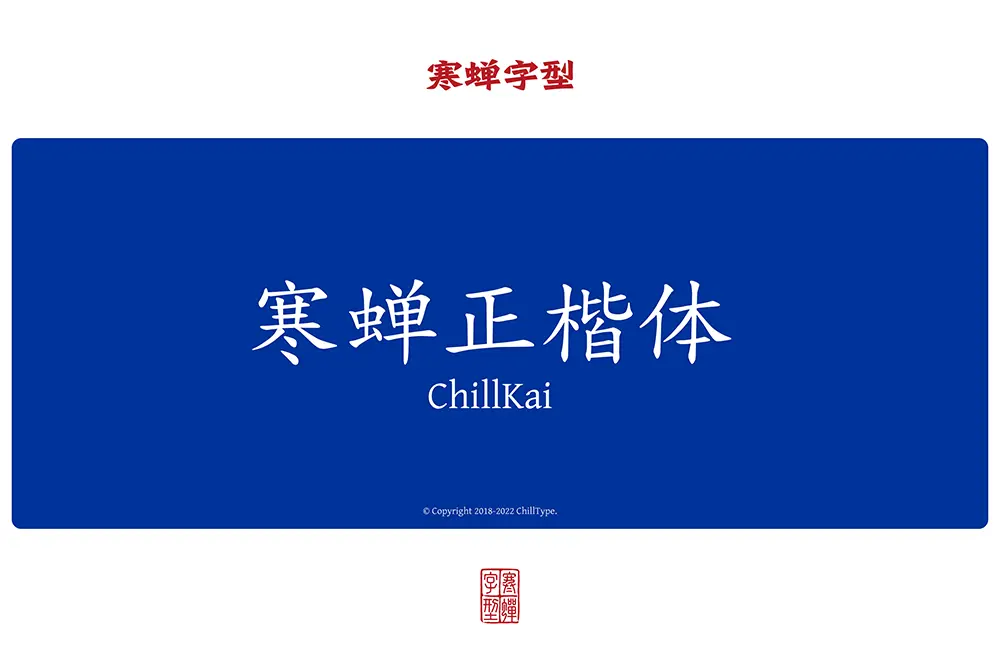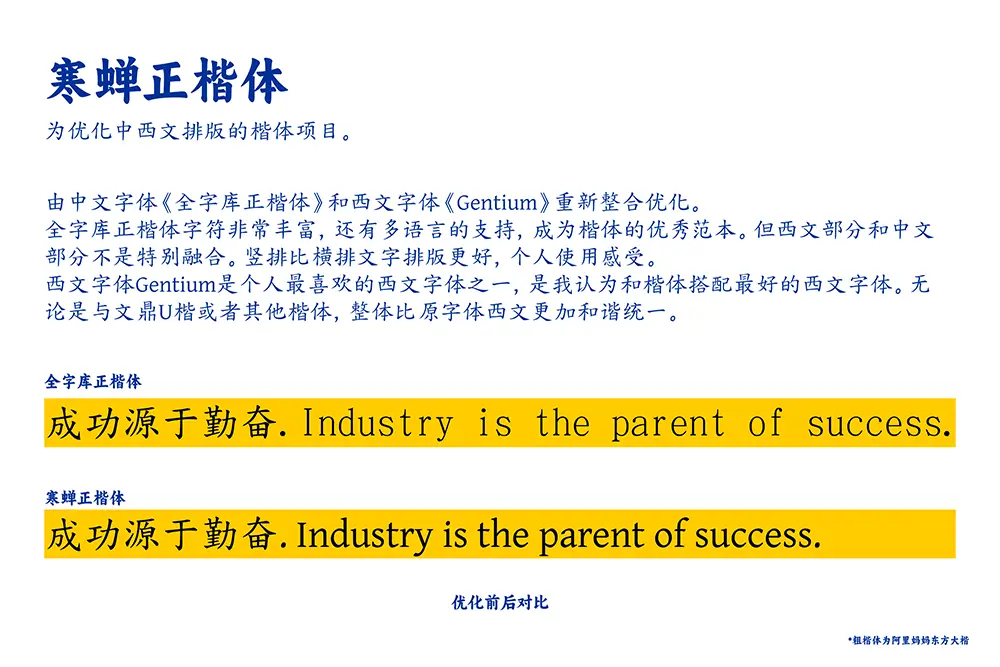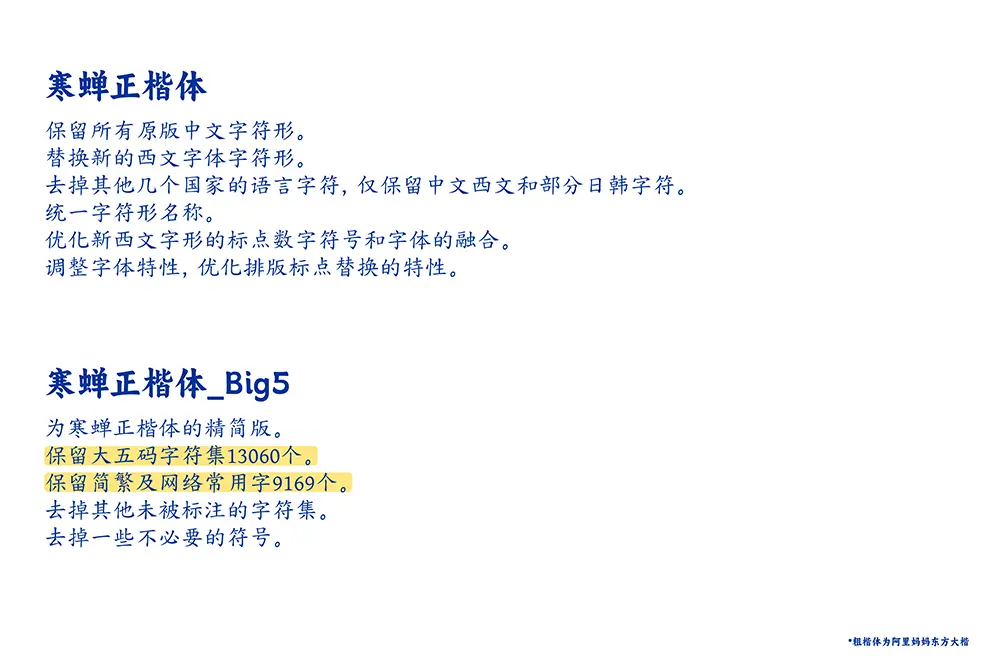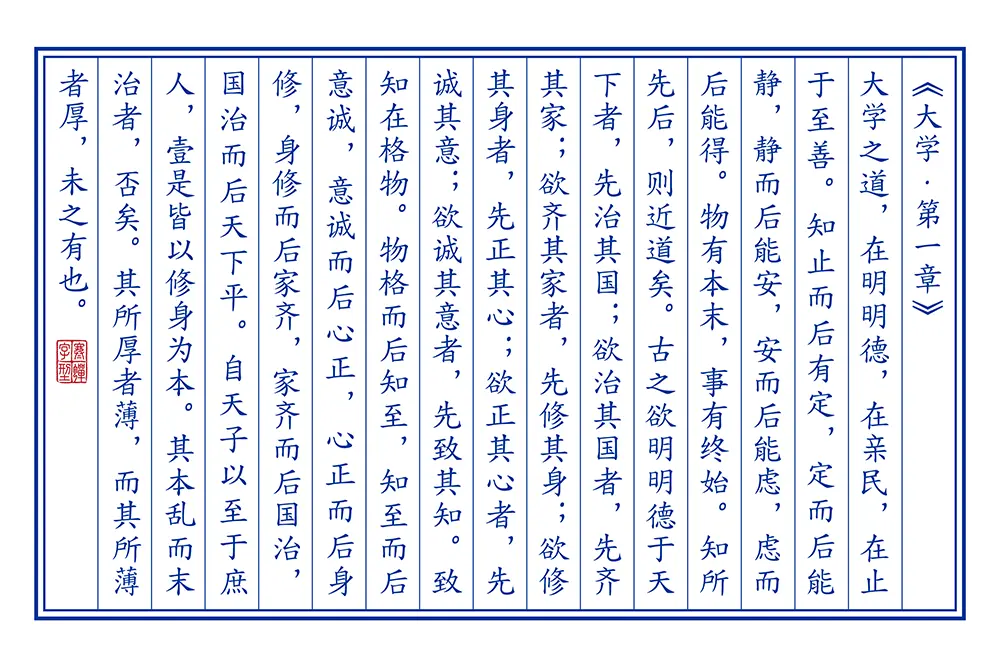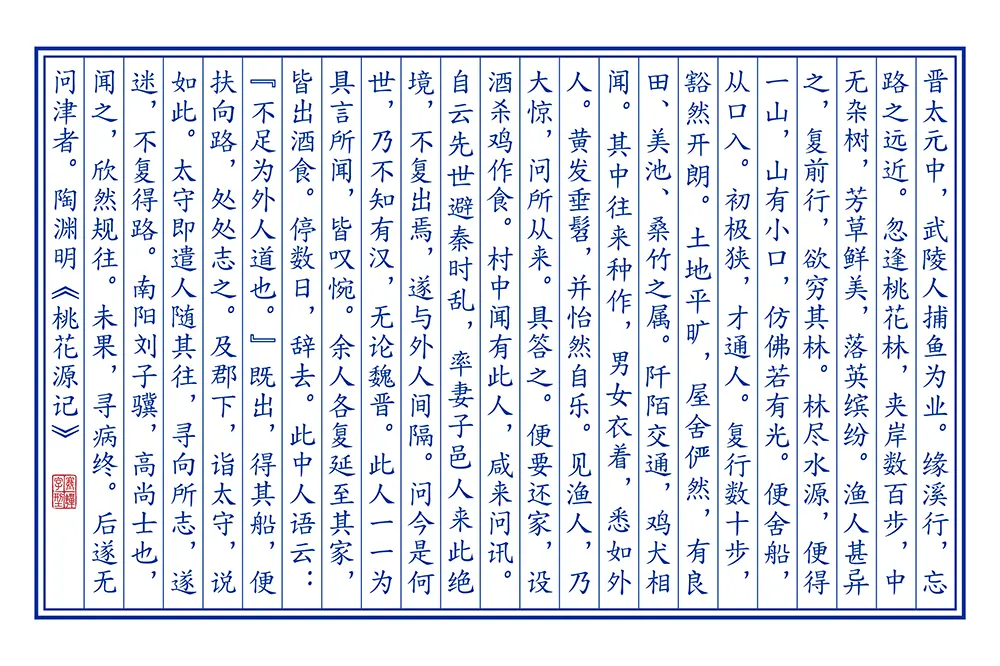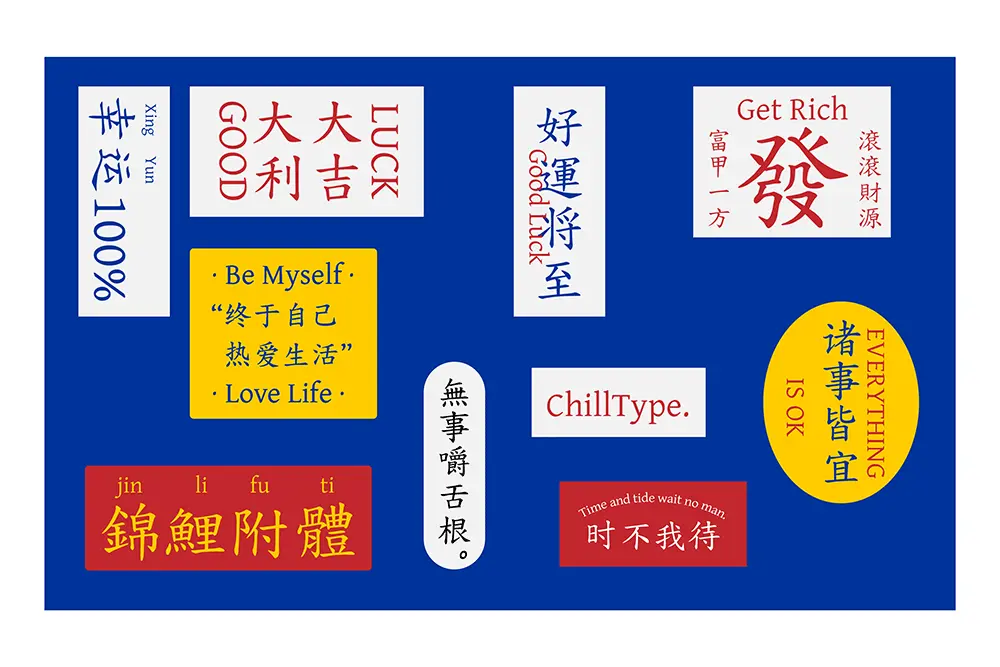
寒蟬正楷體預覽
寒蟬正楷體介紹
寒蟬正楷體(Chillkai)是一個為優化中西文排版的楷體項目,由中文字體《全字庫正楷體》和西文字體《Gentium》重新整合優化。
全字庫正楷體字符非常豐富,還有多語言的支持,成為楷體的優秀範本。但西文部分和中文部分不是特別融合。豎排比橫排文字排版更好,個人使用感受。
西文部分Gentium是個人最喜歡的西文字體之一,是我認為和楷體搭配最好的西文字體。無論是與文鼎U楷或者其他楷體,整體比原字體西文更加和諧統一。